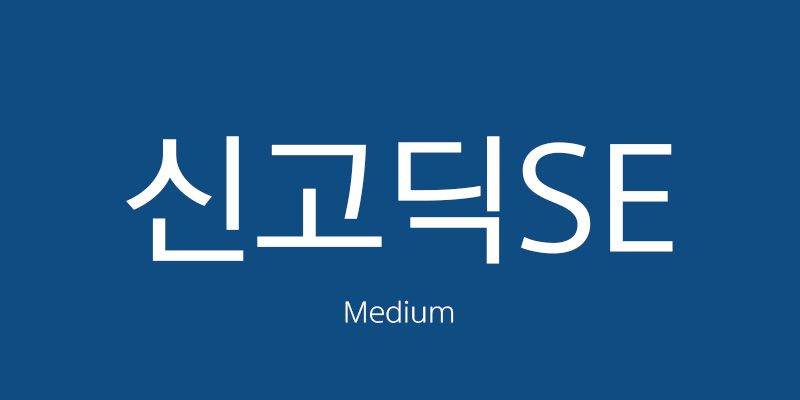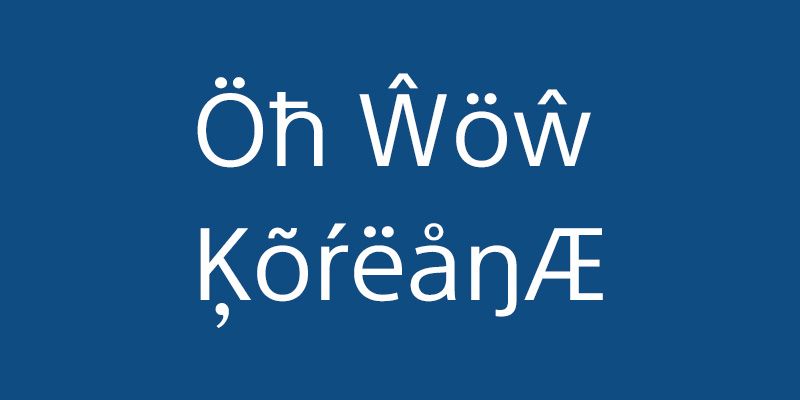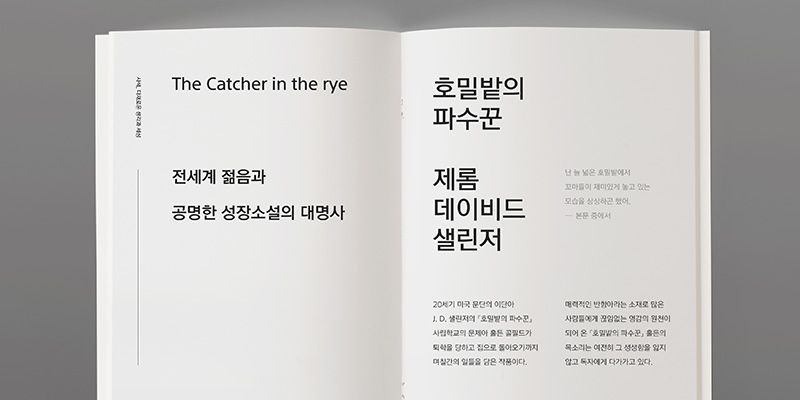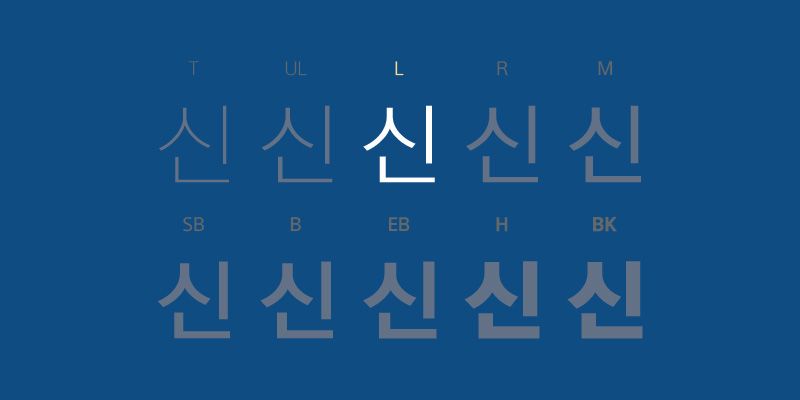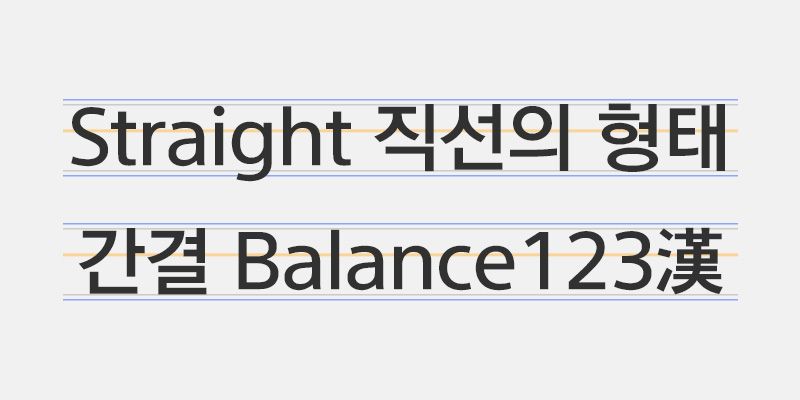
Tout en conservant la structure solide et le haut niveau d’exhaustivité qui sont les points forts de la police Shin Gothic, cette police a affiné le module pour stabiliser davantage l’esthétique, en plus de fournir une extension des caractères latins pour plus de convivialité.